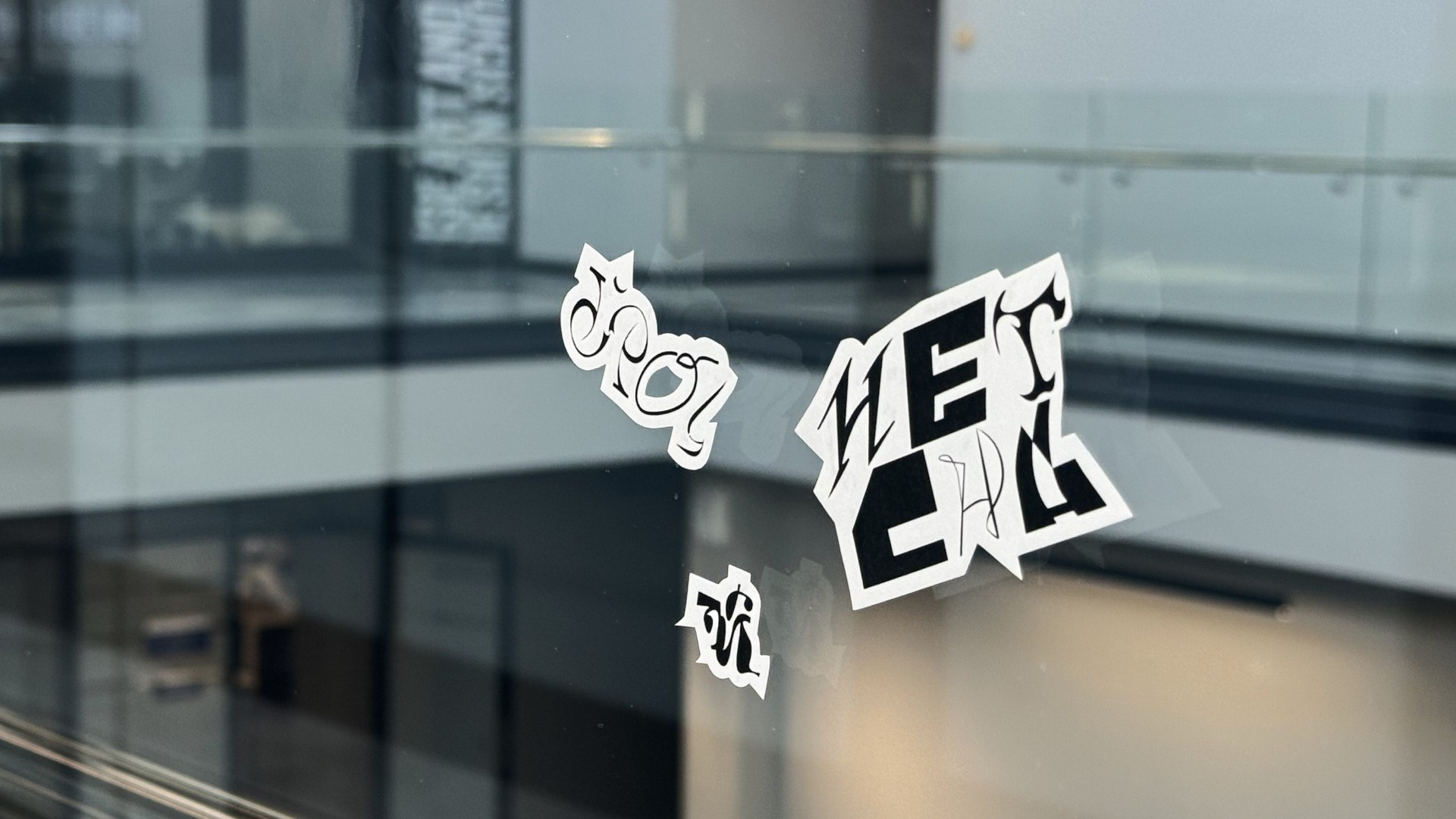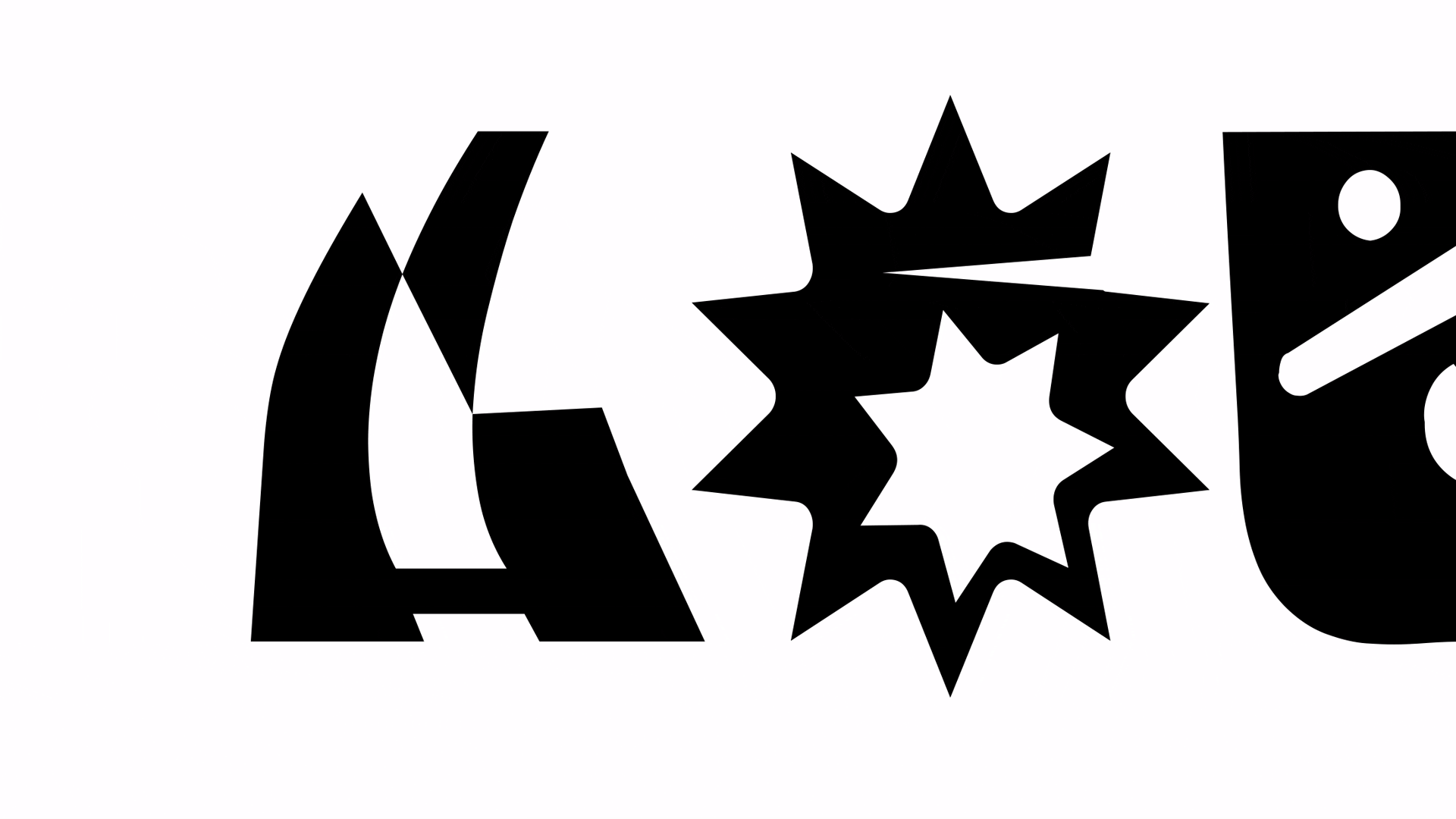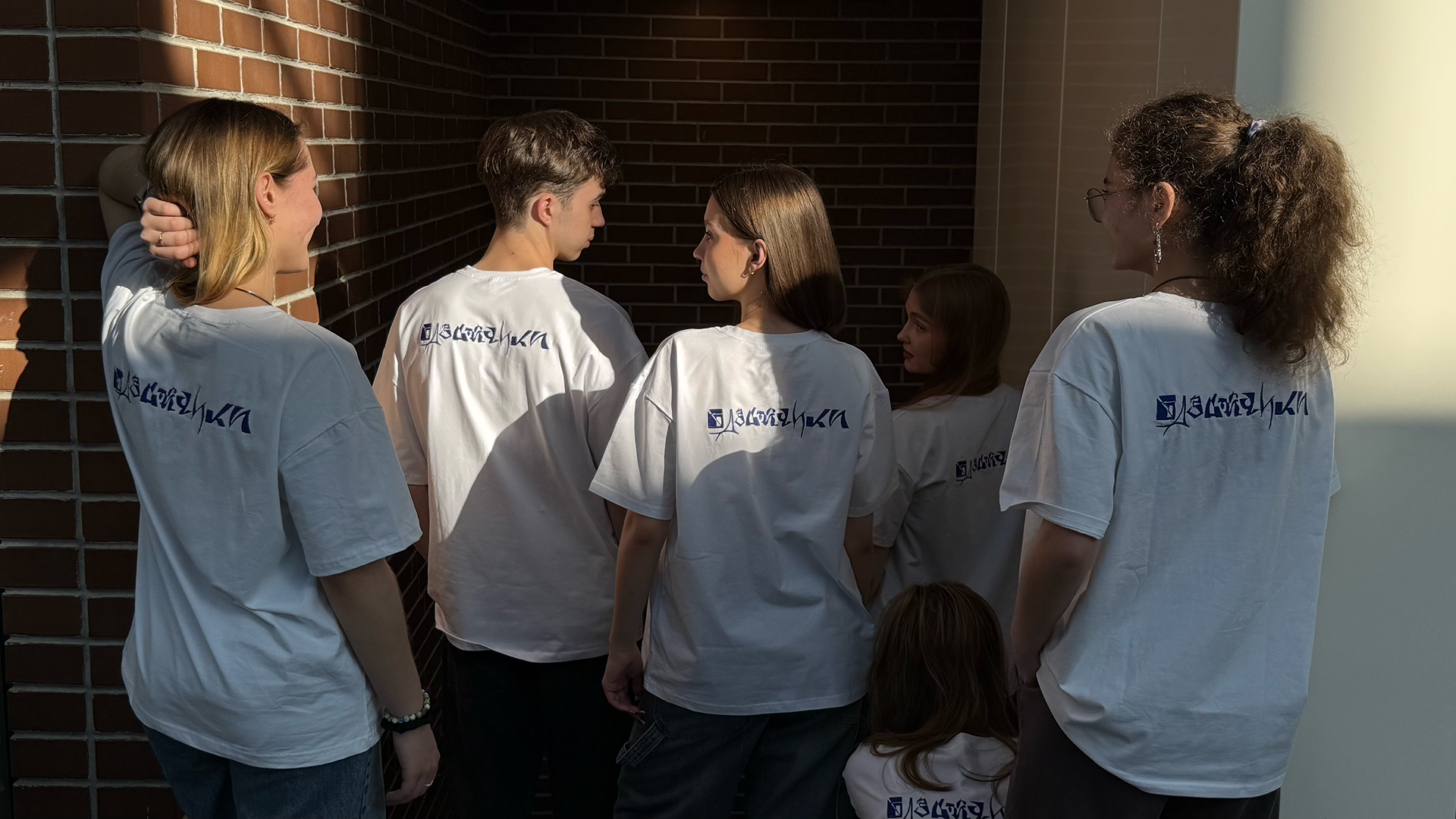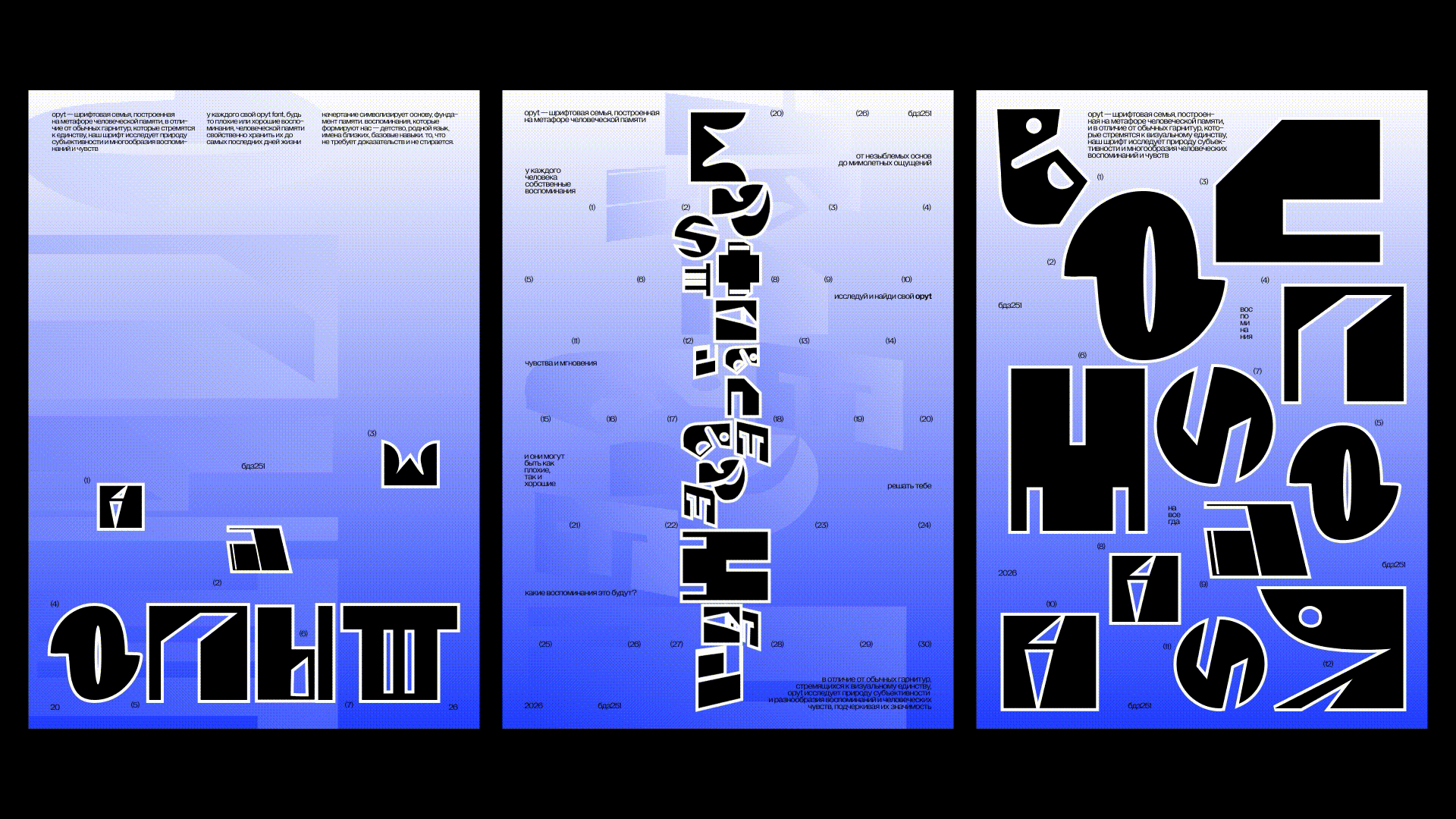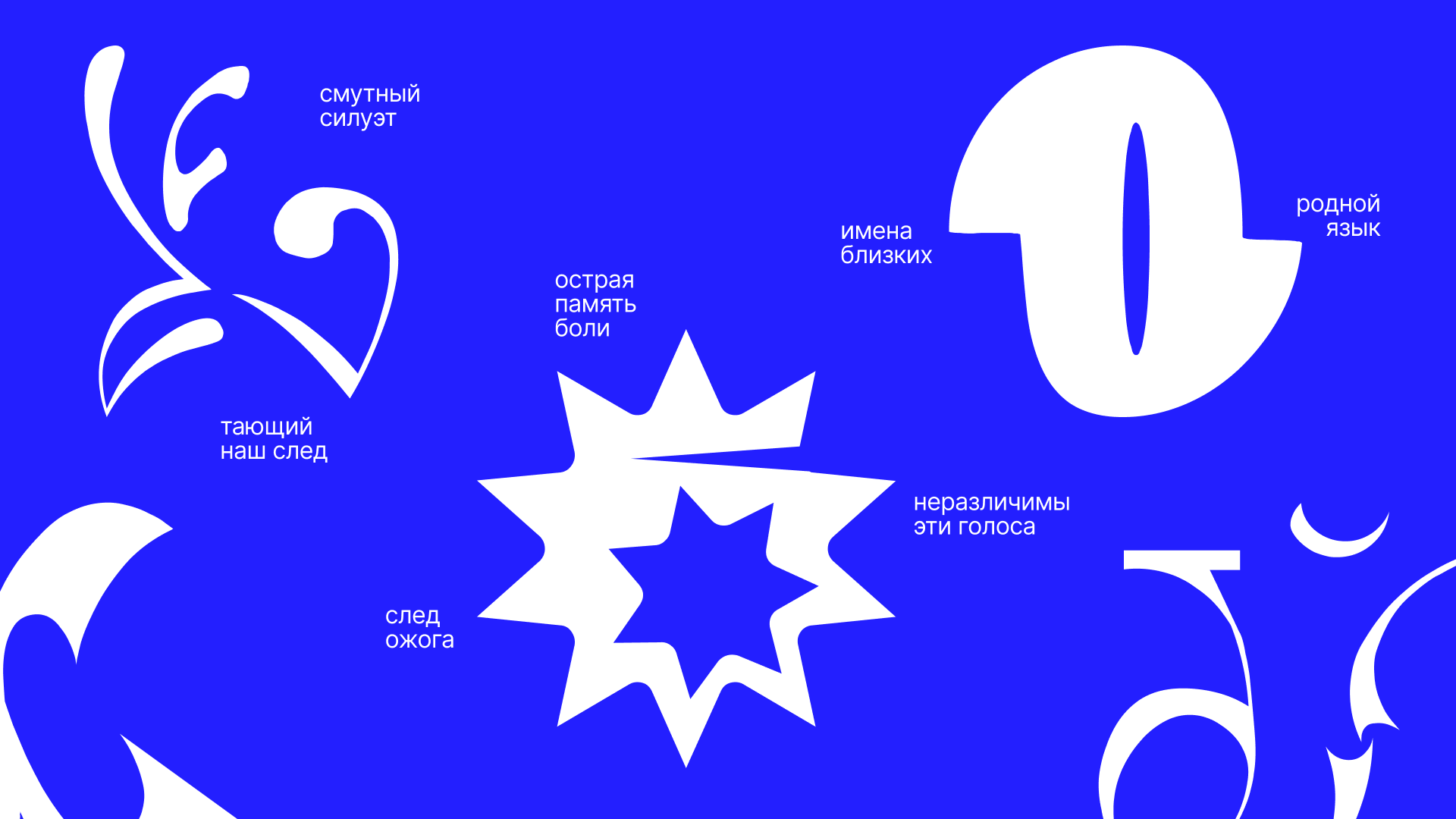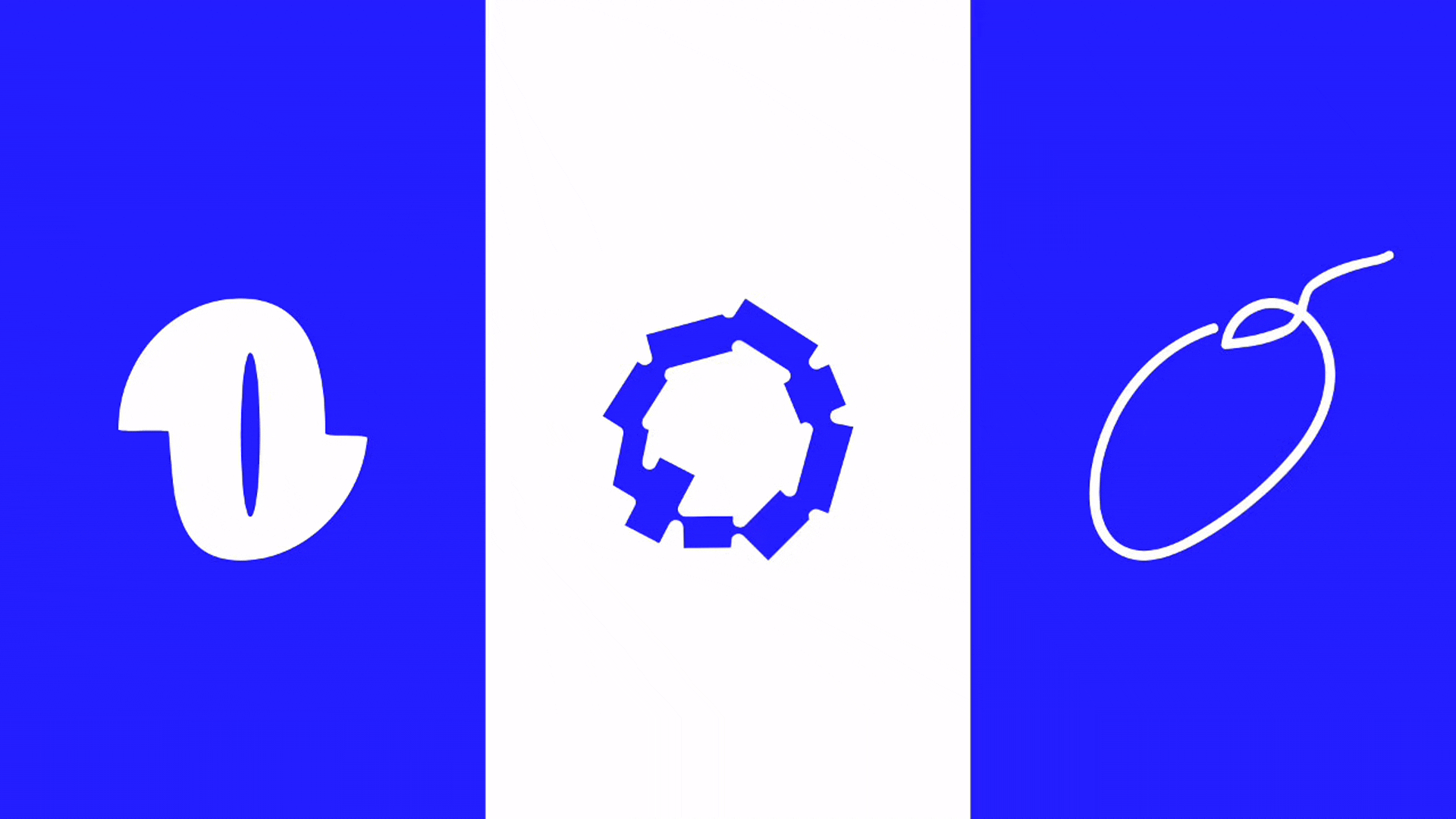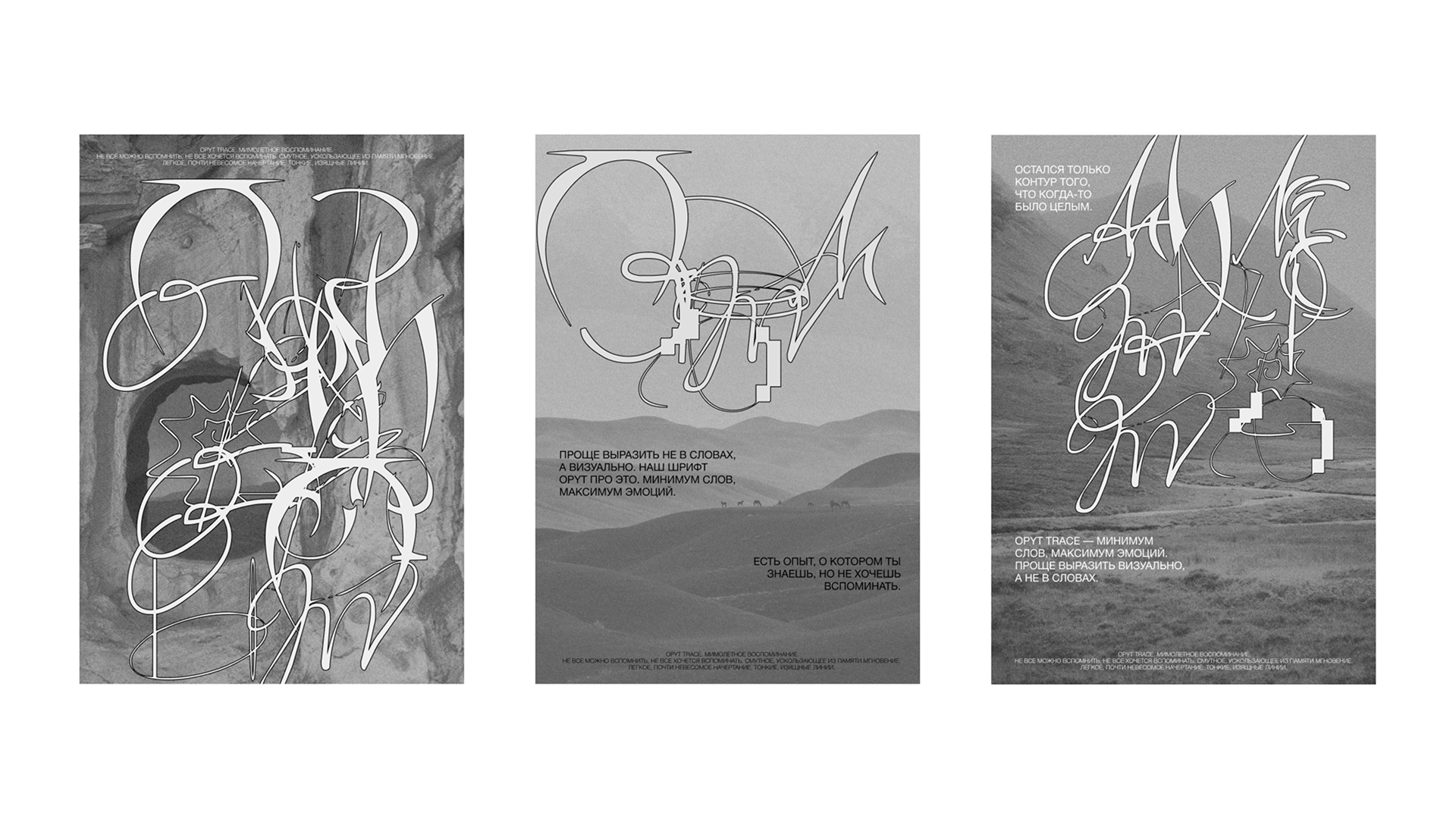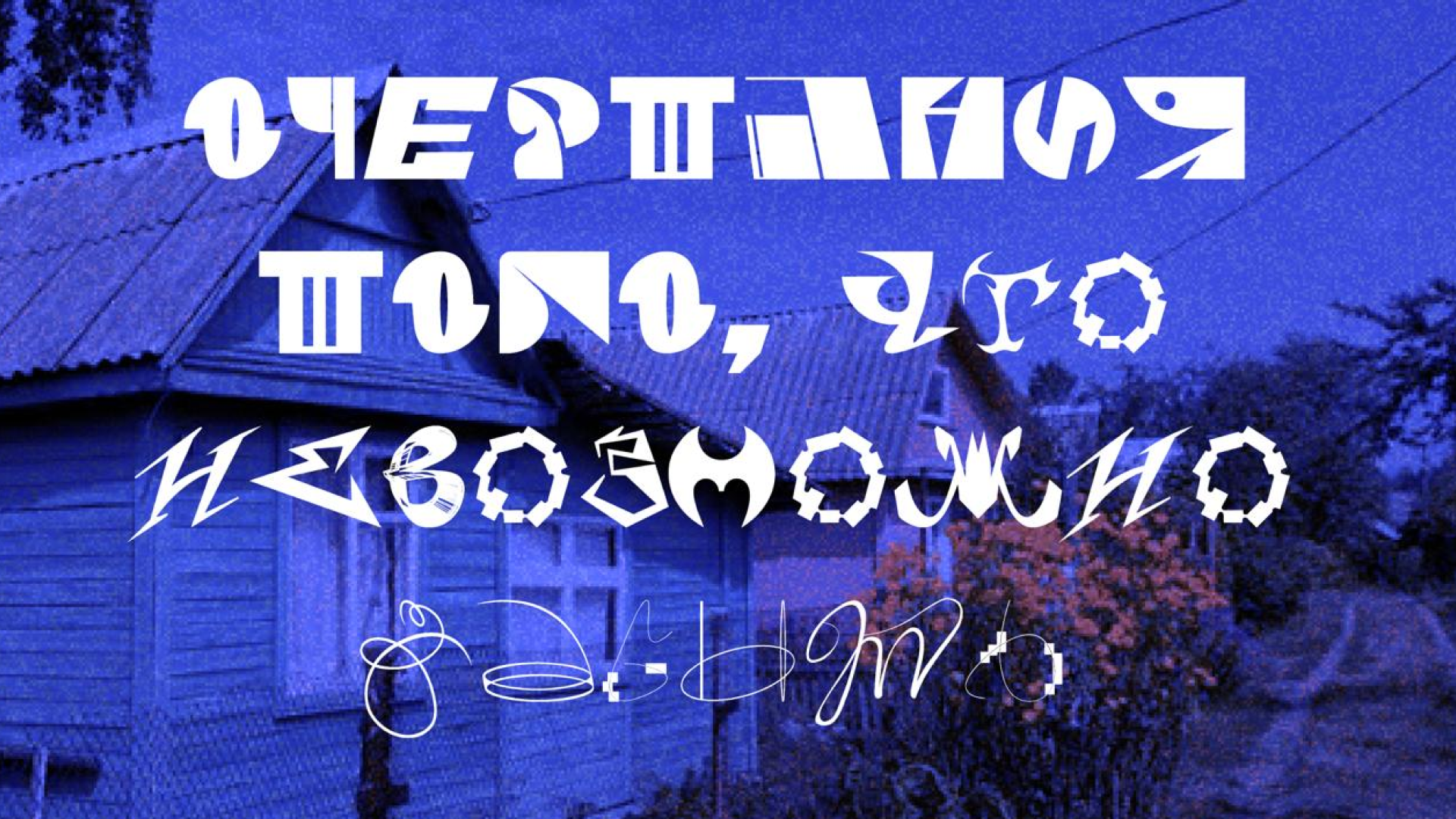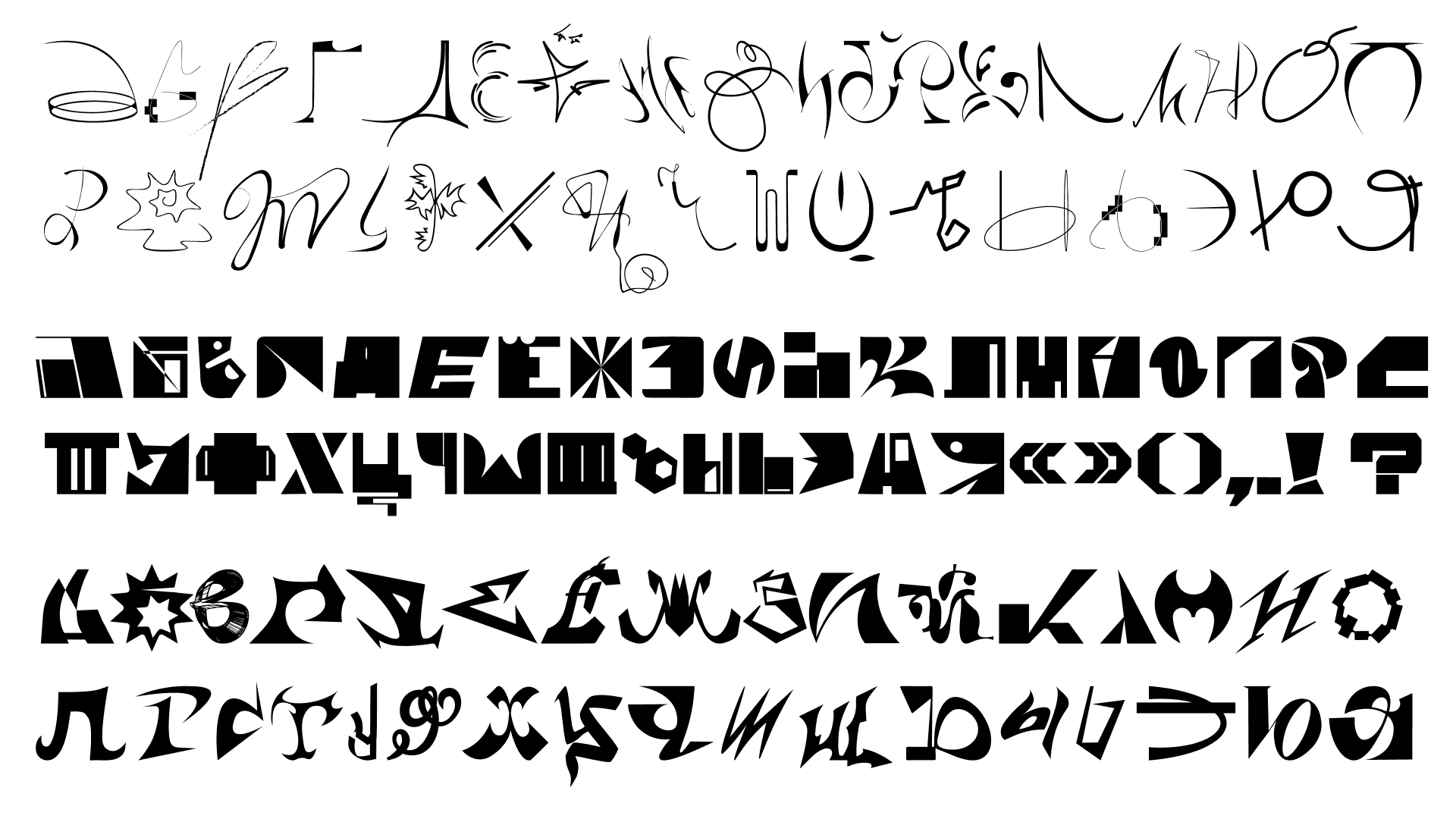
Экспериментальный шрифт
Шрифт ОПЫТ
ОПЫТ - шрифтовая семья, построенная на метафоре человеческой памяти.
В отличие от традиционных гарнитур, стремящихся к визуальному единству, шрифт «ОПЫТ» исследует природу субъективности и разнообразия, а также объединяет в себе хаотичность и серийность начертаний. Одни воспоминания засели в наших головах на долгие годы, другие же постепенно стираются, пока от них не останется лишь далекая неуловимая ясность.